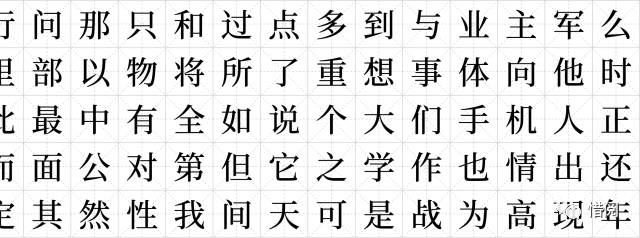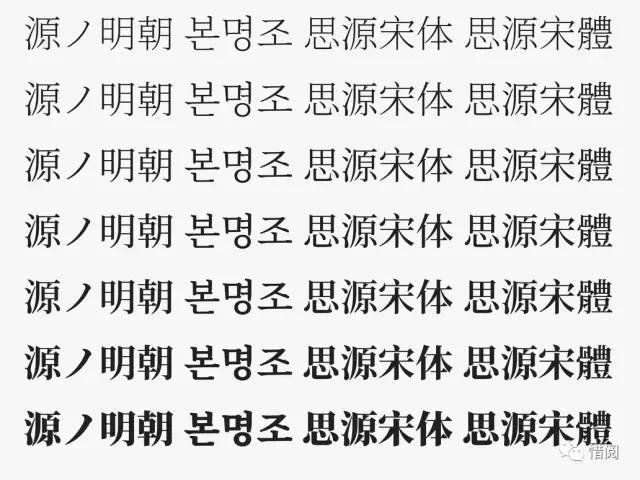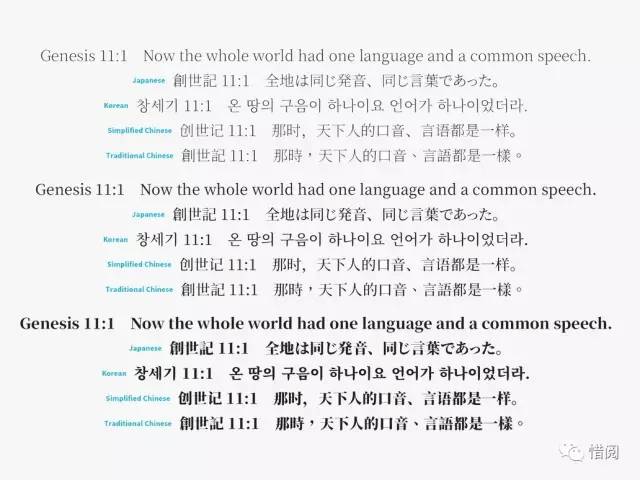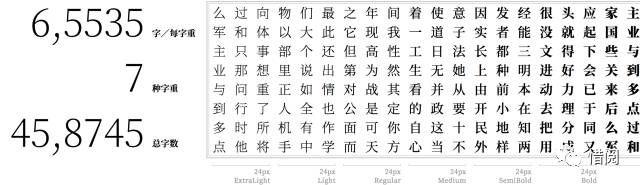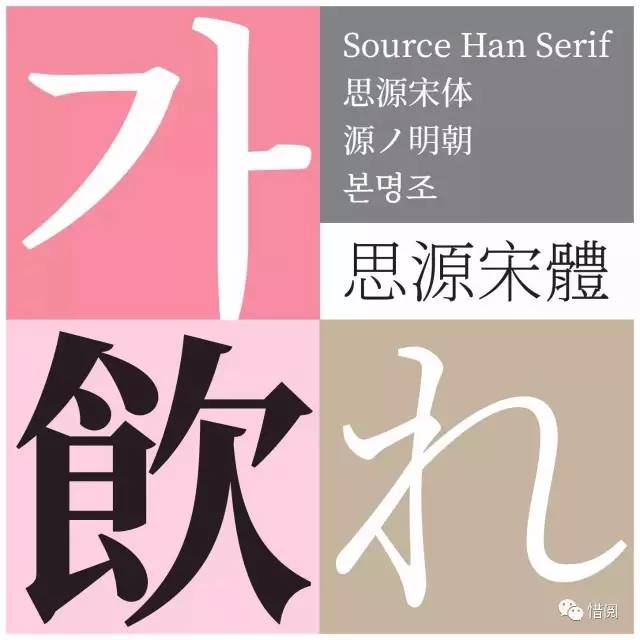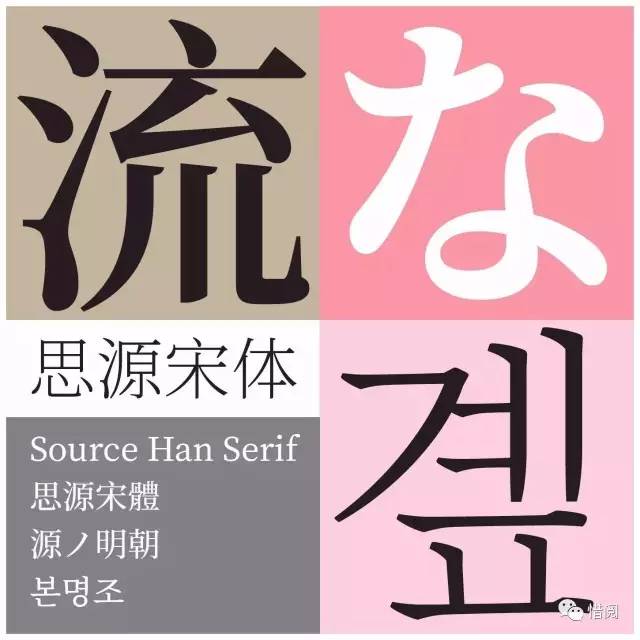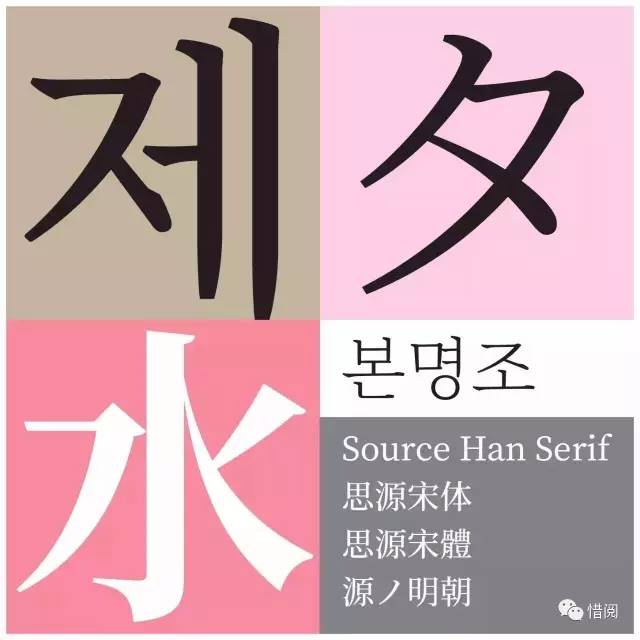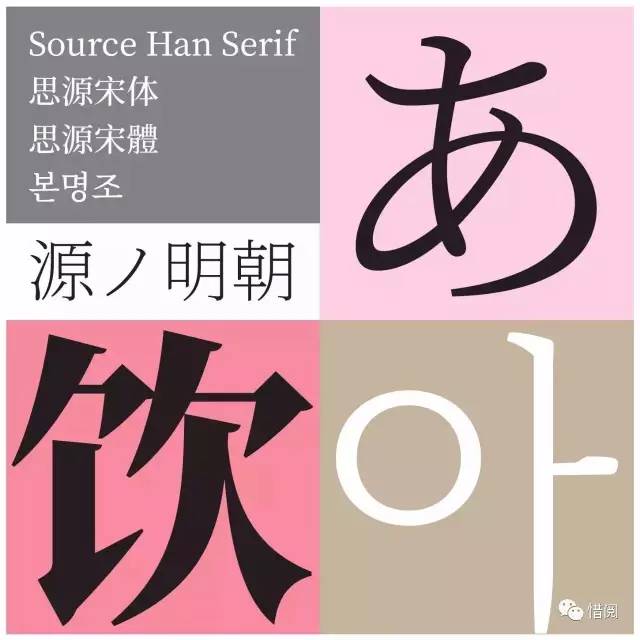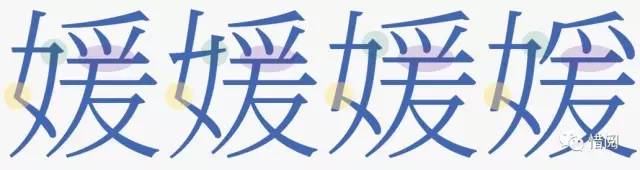
思源黑体之后,Adobe联合Google再推一款免费字体:思源宋体
思源宋体是 Adobe Type 发布的最新泛 CJK 字体,它是对应于思源黑体的宋体字体;我们发布这两种字体是为了响应统一设计的需求,以服务于东亚 15 亿人口。
思源宋体支持四种不同的东亚语言(简体中文、繁体中文、日语和朝鲜语),7 种粗细类型中的每一种都有 65,535 个字形,可共同呈现一致的视觉美感。该字体还包含多个西方字形,支持拉丁语、希腊语和西里尔文脚本,这些字形均来源于 Source Serif。
完整 Source Han 字体系列远远超出了普通 “超系列” 字体的范畴,它是 Adobe 与 Google 之间的大量合作以及合作伙伴公司(中国的常州华文、韩国的 Sandoll Communications、日本的 Iwata Corporation)参与的成果。这些字体以开源许可证形式在 GitHub 上发布。
思源黑体和思源宋体项目的成功离不开我们与 Google 的合作关系,Google 帮助我们启动此项目,并且提供了指导、测试资源和财务支持。思源黑体和思源宋体字体集成到 Google 的泛 Unicode 字体系列(称为 Noto)中。
“Google Noto 字体项目的目标是为所有现代设备开发一款涵盖所有语言的和谐、优质的字体系列,无论是从规模还是范围的角度来看,这都是一项极其艰巨的任务。” Google 国际化总监 Bob Jung 说,“仅 CJK 语言就对超过 10 亿用户有着至关重要的意义。Adobe 作为数字排版的先锋,是帮助我们将优美的 CJK 引入 Noto 中的理想合作伙伴。”
“此次发布对于多语言设计者来说非常重要。”Sandoll 的 CEO Geumho Seok 说,“这些字体能够实现‘消灭豆腐块’的目标,意思是 Unicode 字体不会在排版中出现空白字形。”
在有些情况下,基于同一个原始表意文字的字可能有多达四个区域差异化的字形设计。思源宋体涵盖所有这些字形变体并且精心地设计了这些区域化字形。您只需选择相应语言特定的字体或相应的语言标签,正确的字形变体就被设置成功了。
思源宋体也和它的兄弟字体思源黑体一样针对屏幕显示进行了优化,但前者具有截然不同的风格,适合用于文学性较强的文本或优雅、时尚的标题。它的打印效果也非常优美。通过 Typekit 同步字体可让您使用同一种字体即时呈现多种语言,并且在任何带有字体选择菜单的桌面应用程序中使用这些字体。
思源宋体有7种不同字重,可以满足各种各样的字体排印需求。
创造思源宋体需要各方进行大量协作,没有合作伙伴的支持,我们就不可能完成它。这个简短视频概括和回顾了在创造一款真正国际化字体的项目中,每个合作伙伴需要付出的长年累月的努力。
思源宋体的故事
字体作者
Source Han 字体系列的项目设计师 Ken Lunde 博士从事大量繁重的工作,处理了近 50 万字形及其关联元数据,将它们变成功能完备的泛 CJK 字体。
Ryoko Nishizuka (西塚涼子)是 Adobe 在东京的首席字体设计师,领导了思源宋体中的表意文字块、日语假名和其他日语字符的字形设计。她曾为思源黑体做过相同的工作;在这款字体发布后不久的 2014 年采访中,她向我们讲述过自己的设计过程。
同样来自 Adobe 字体团队的字体设计师 Frank Grießhammer 设计了拉丁文、希腊语和西里尔文字形,这些字形包含在思源宋体中,也作为它们自己的字体 Source Serif 存在,该字体的最新更新在今年 1 月发布。由于拉丁文字形设计只有经过专门的调整才能支持思源宋体,因此 Frank 在开始 Source Serif 设计过程的早期就与 Ryoko 进行过协商。